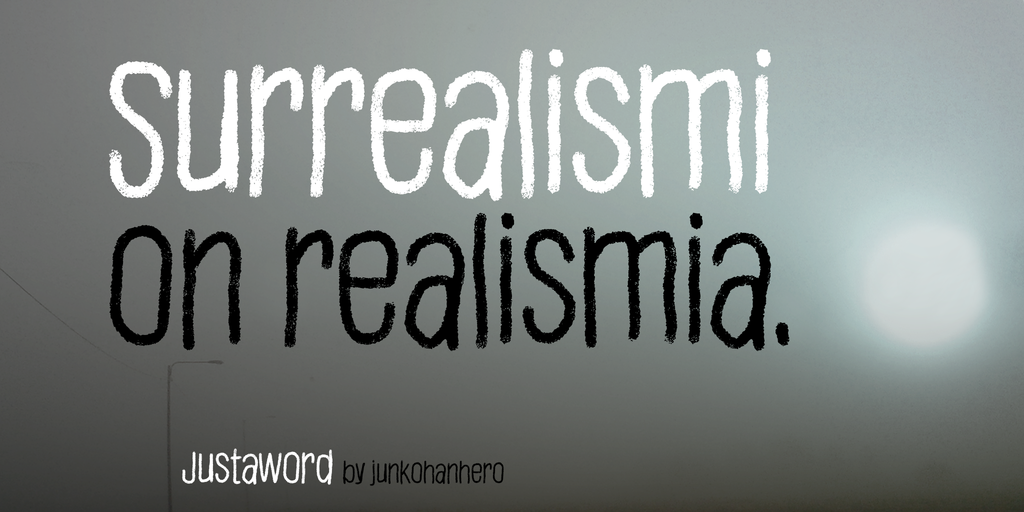
Justaword Font
Estamos muito felizes por você decidir adicionar a ‘Justaword Font’ à sua próxima projeto visual. Esta fonte manuscrita é perfeitamente adequada para criar textos pessoais, cartas e até mesmo pequenos projetos DIY. A Hamilton criou uma fonte única e autêntica que convida ao trabalho artístico manual. Ela se destaca por suas tramas fluidas e nuances suaves que adicionam um toque de personalidade à qualquer texto usado. Se você estiver trabalhando em um projeto comercial, sabemos o quanto isso pode exigir tempo e recursos. Se desejar utilizar a ‘Justaword Font’ para fins comerciais, você pode fazer seu pedido por 15€ ou $20 através do PayPal. Após receber sua confirmação financeira, enviar-nos uma mensagem de email para confirmar que tudo está em ordem. Você também tem a opção de fazer um depósito regular se isso melhor atender suas necessidades. Nossas fontes são gratuitas para uso pessoal e nós valorizamos muito a nossa comunidade de criativos. Estamos aqui para apoiar você ao máximo, então não hesite em entrar em contato sempre que precisar de ajuda ou tiver alguma dúvida sobre como usar nossas fontes.